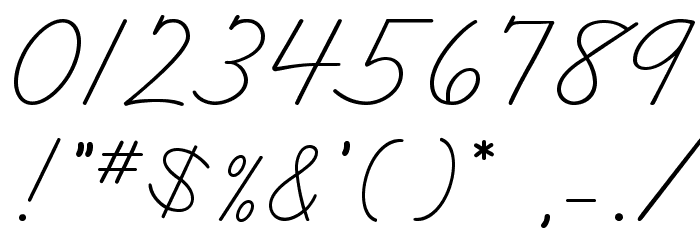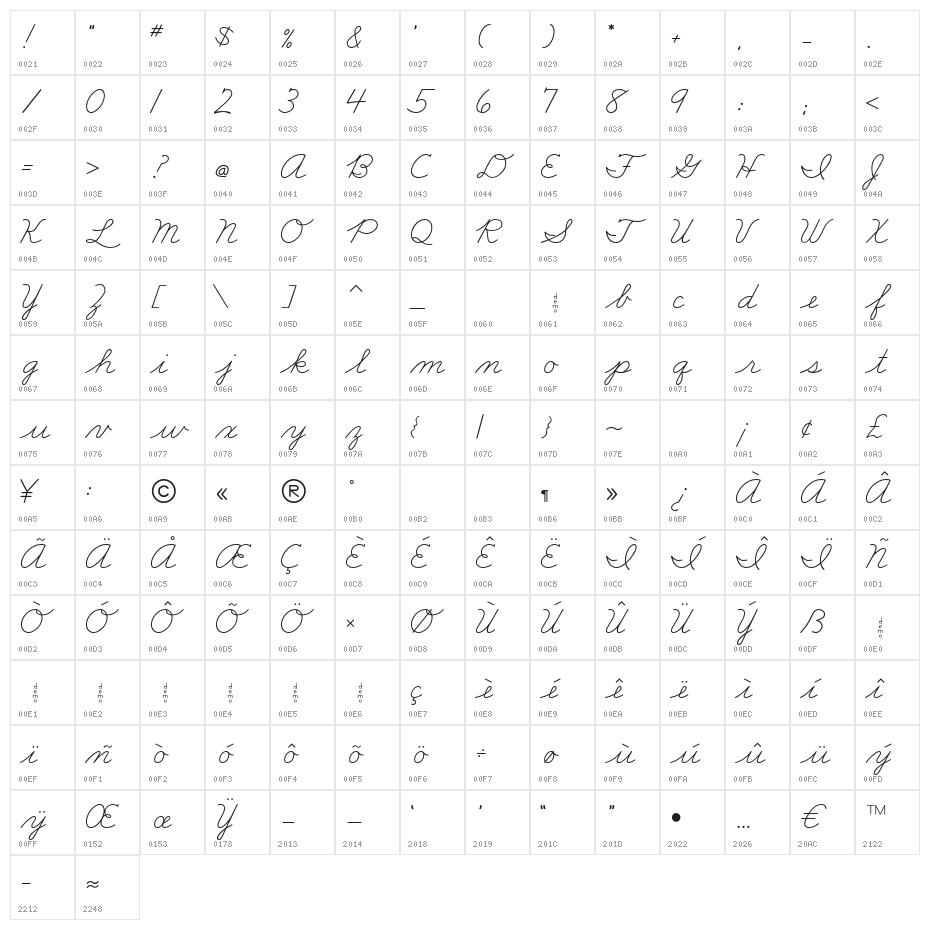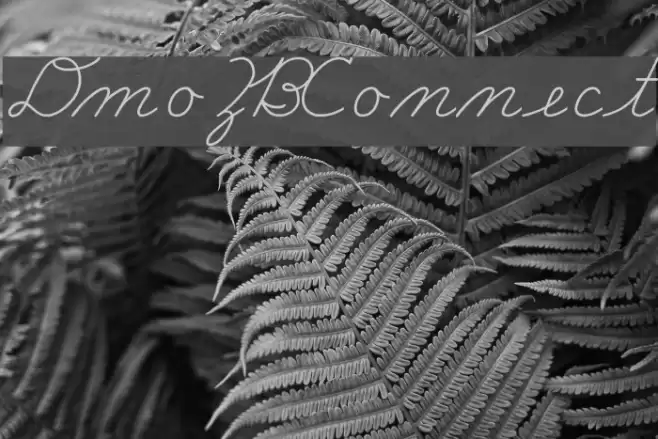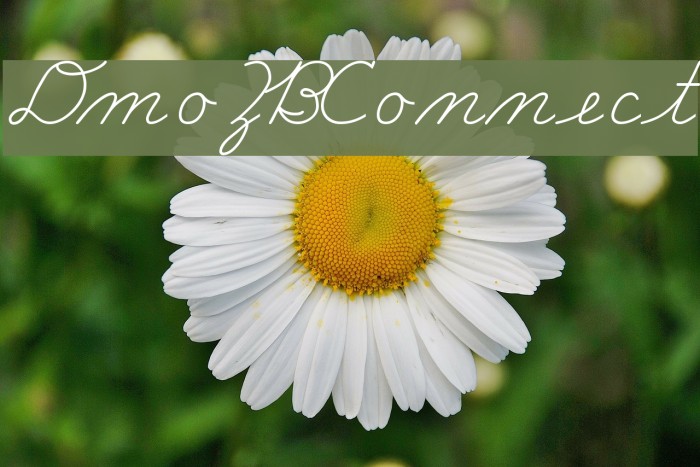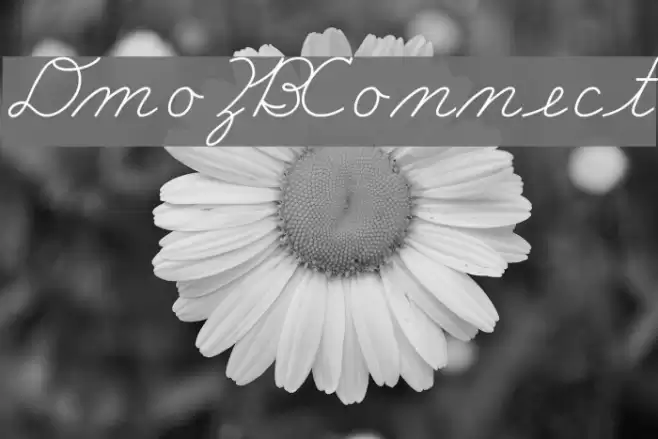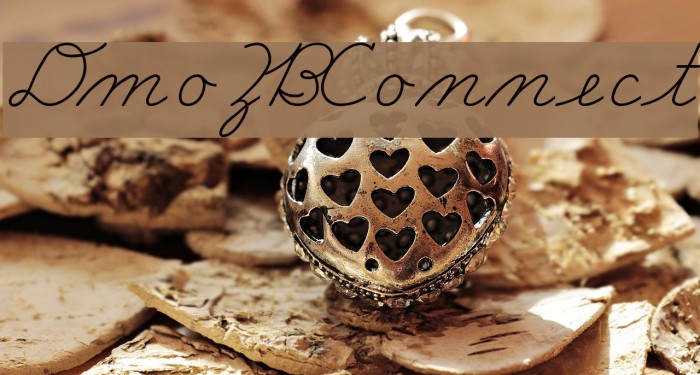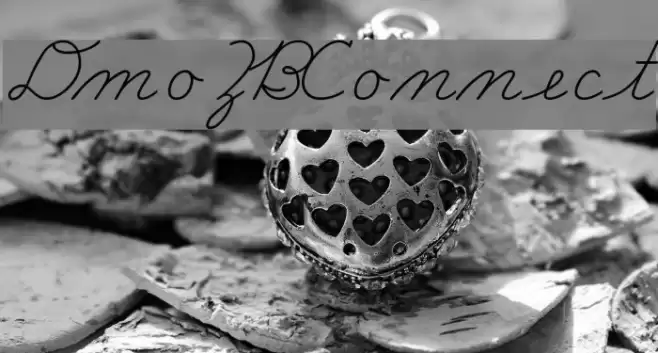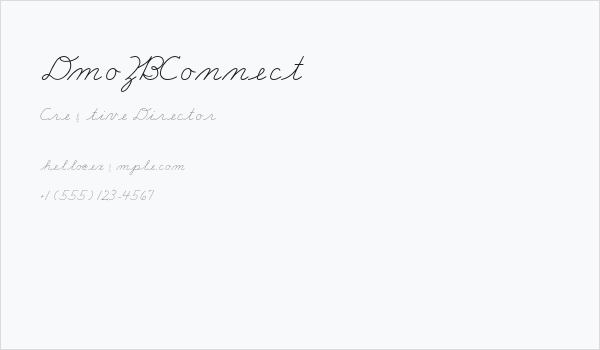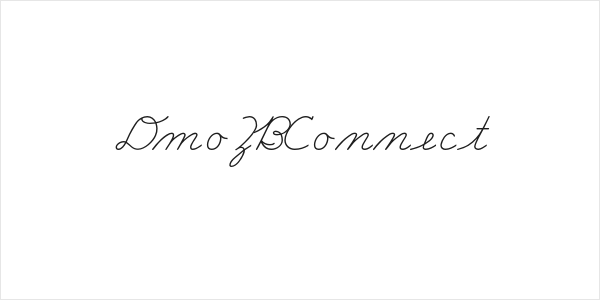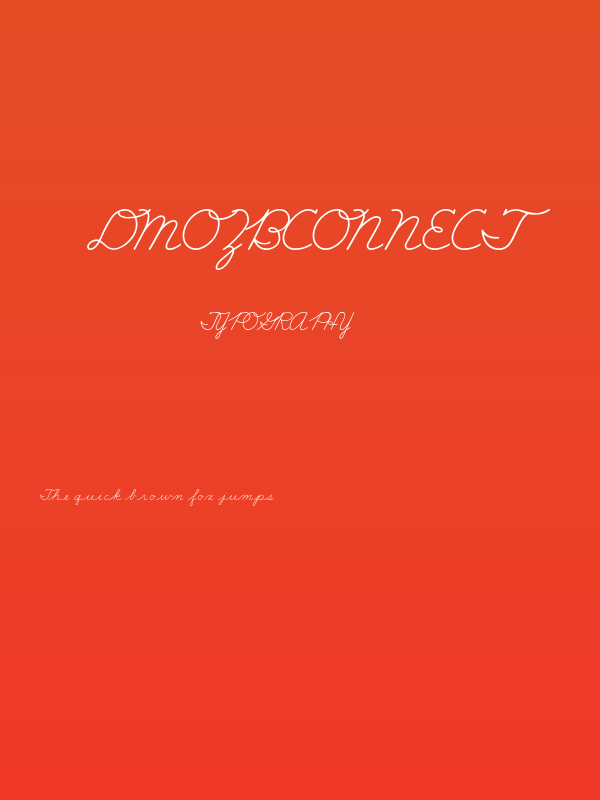
DmoZBConnect Font
| Gesamtstil | Elegant |
| Anwendungsfall | Logos, Invitations, Personal Branding |
| Vorgeschlagene Projekte | Ideal for wedding invitations, greeting cards, personal branding, and elegant packaging designs. |